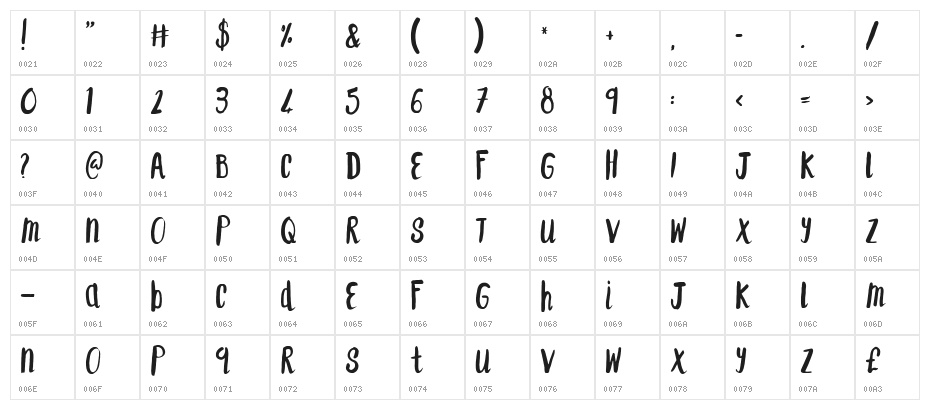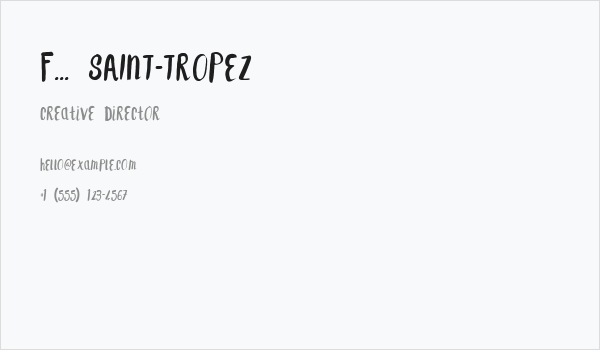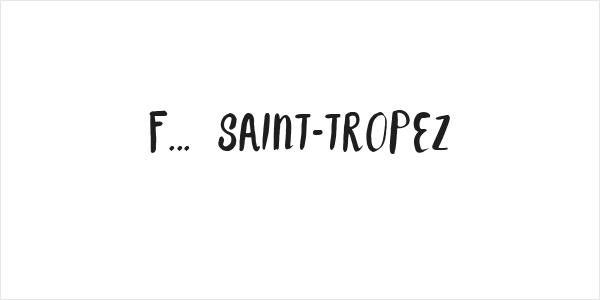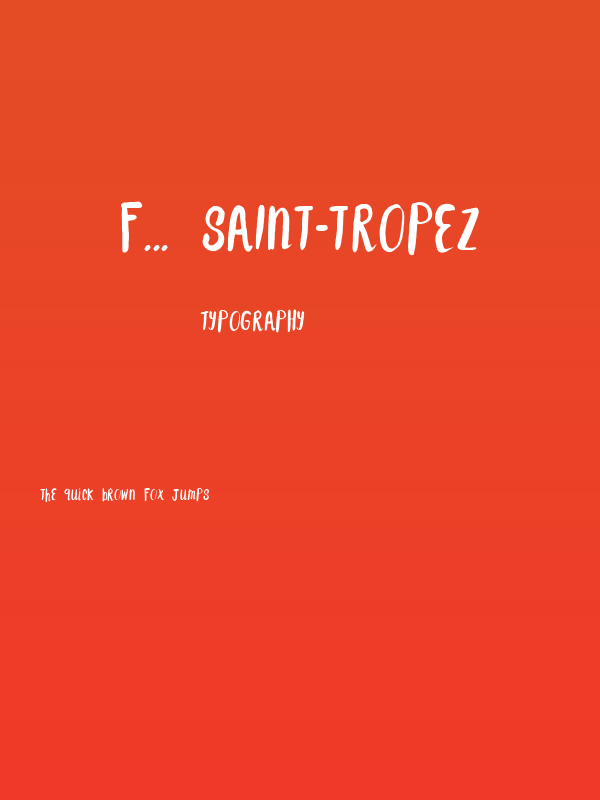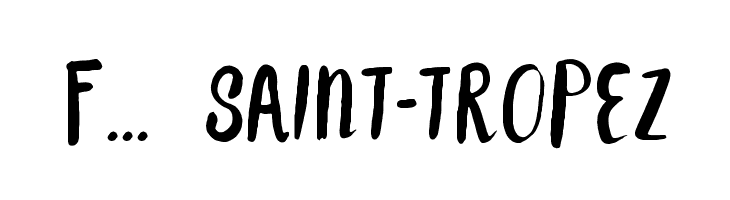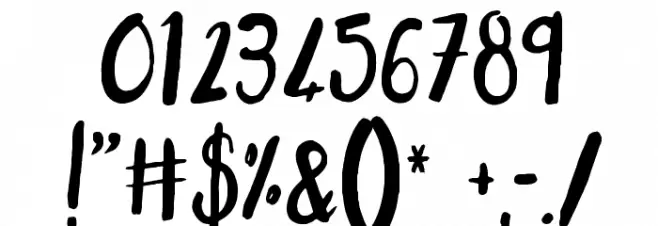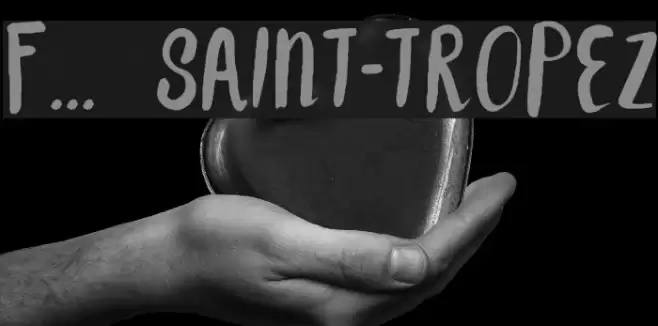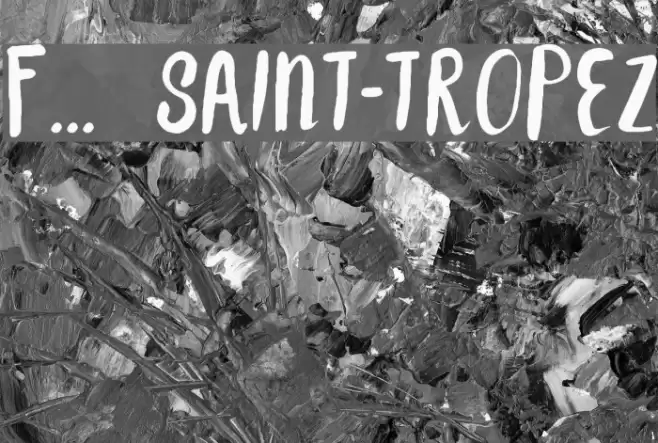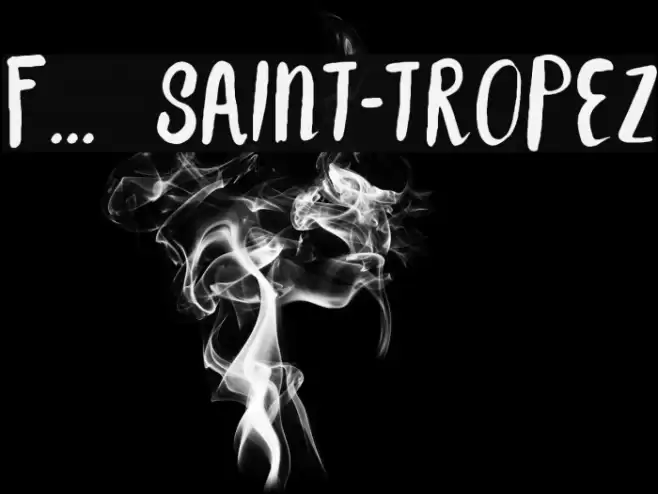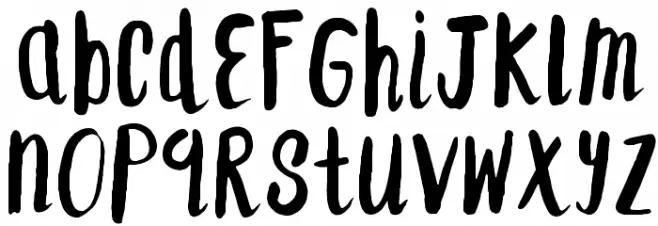
F... SAINT-TROPEZ Font
| Kategorien | Script |
| Gesamtstil | Casual, Artistic |
| Anwendungsfall | Headlines, Logos, Creative projects |
| Vorgeschlagene Projekte | Ideal for greeting cards, invitations, children's books, and creative branding projects. |